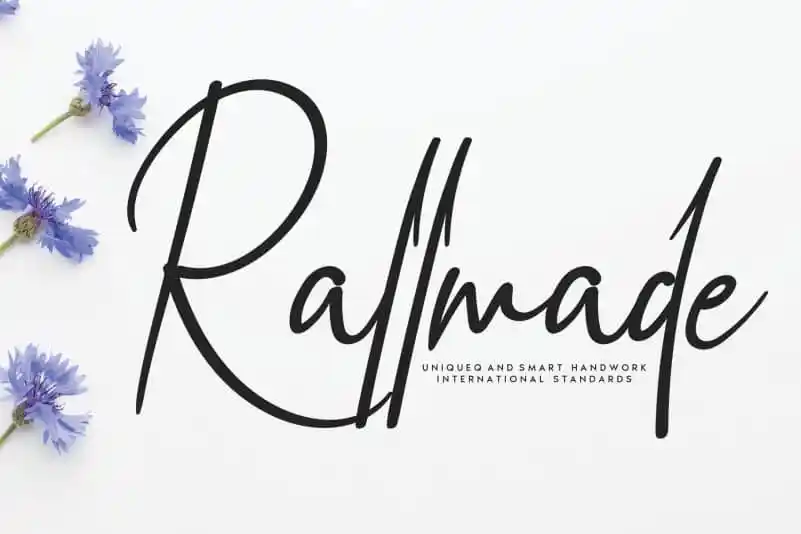
Rallmade Script Font – Download Grátis
A Rallmade Script Font é uma hermosa fónt que se encontra no universo do estilo manual e aveludado, projetada para quem busca uma graça natural na sua tipografia. Esta fonte tem um toque elegante, pronta para decorar qualquer projeto favorito. Seu design único e inigualável faz dela uma escolha ótima para aqueles que buscam deixar suas criações mais memoráveis e estilosas. A Rallmade Script Font é perfeita para adicionar um toque especial em anúncios, cartões de Natal personalizados ou até mesmo gráficos publicitários. Seja qual for o seu projeto, a Rallmade Script Font tem o poder de torná-lo destoante e único.